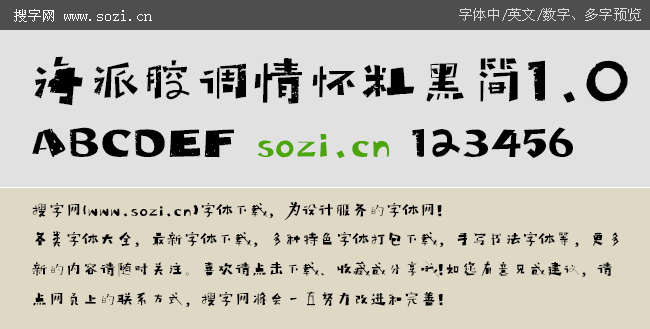
海派腔調(diào)情懷粗黑簡1.0
搜字網(wǎng)提供一海派腔調(diào)情懷粗黑簡1.0中文字體下載,海派腔調(diào)情懷粗黑字體是一款左粗右細(xì)、整體效果非常出眾的簡體中文字體,適合應(yīng)用于廣告設(shè)計、名片設(shè)計、包裝印刷、產(chǎn)品設(shè)計等應(yīng)用。